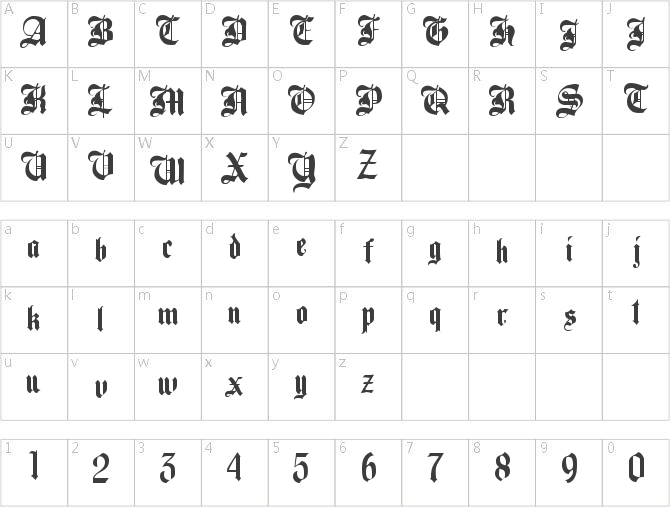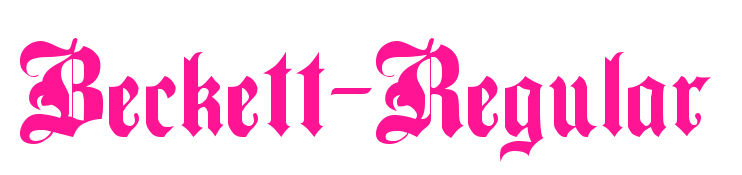
字體名稱(chēng): Beckett
Beckett-Regular
Beckett-Regular字體字庫(kù)是一款讓人賞心悅目、百看不厭的英文字體,適合各類(lèi)廣告和產(chǎn)品包裝設(shè)計(jì)應(yīng)用,字體大小0.04MB,格式為ttf字體,上傳用戶(hù)是澤澤,作者/版權(quán)方為未知